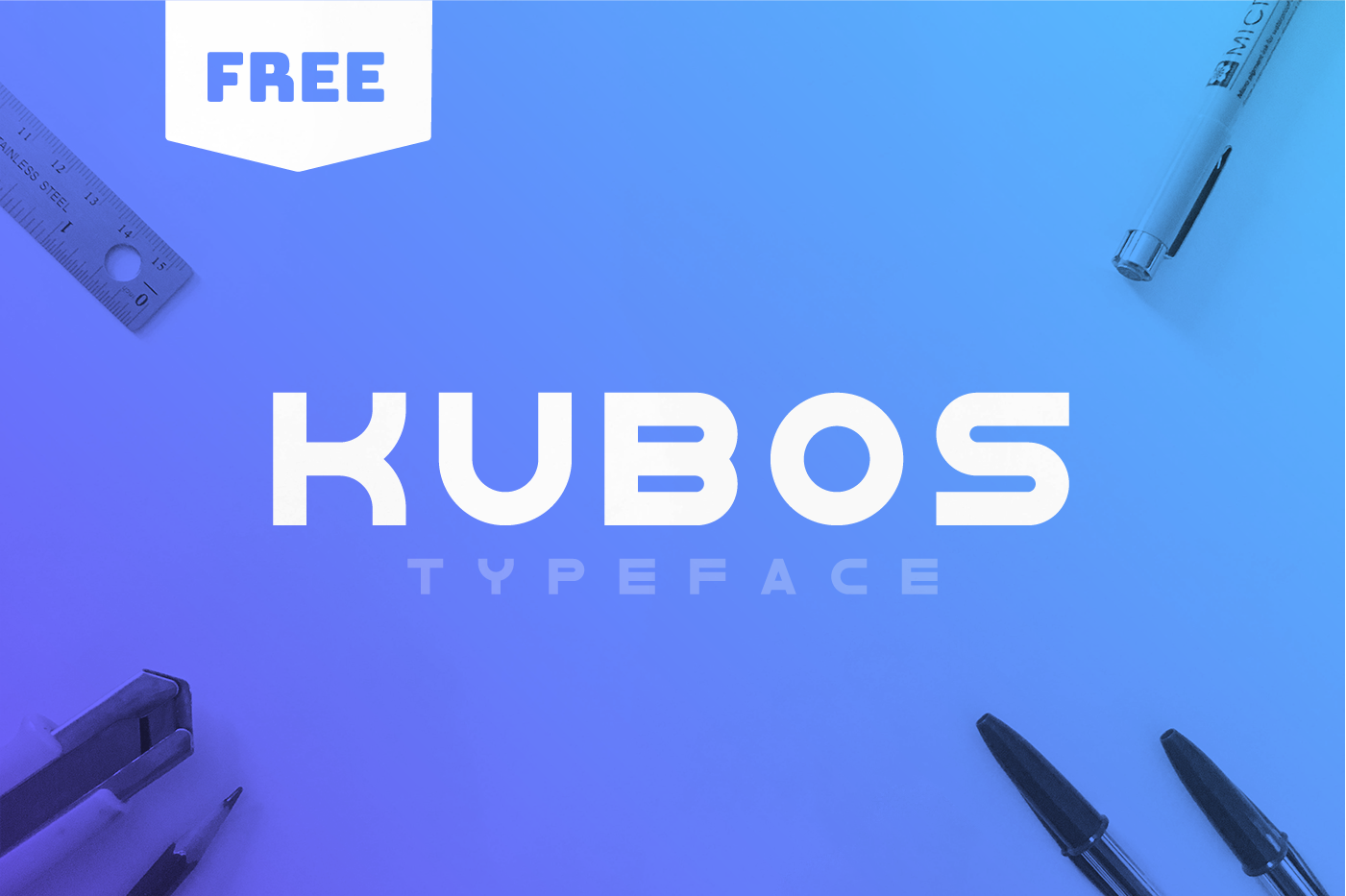
Kubos Display Typeface – Download Grátis
Kubos Display Typeface é uma tipografia sans-serif geométrica moderna que surgiu do grego “κύβος”, traduzindo-se para “cube”. Apesar de sua simplicidade inicial, essa tipografia explora os desafios envolvidos na respeitosa utilização da grade geométrica. Ideal para design gráfico e elementos visuais modernos, Kubos Display se destacará em qualquer projeto que necessite de um equilíbrio entre simplicidade e sofisticação. Seu designer, gy.design, trouxe à vida uma tipografia que transcende a sua superfície aparentemente simples, proporcionando aos designers o poder de criar ambientes visuais arrojados e contemporâneos. Engane-se com essa tipografia, pois ela carrega consigo um refinamento que se destaca em design gráfico moderno e minimalista.